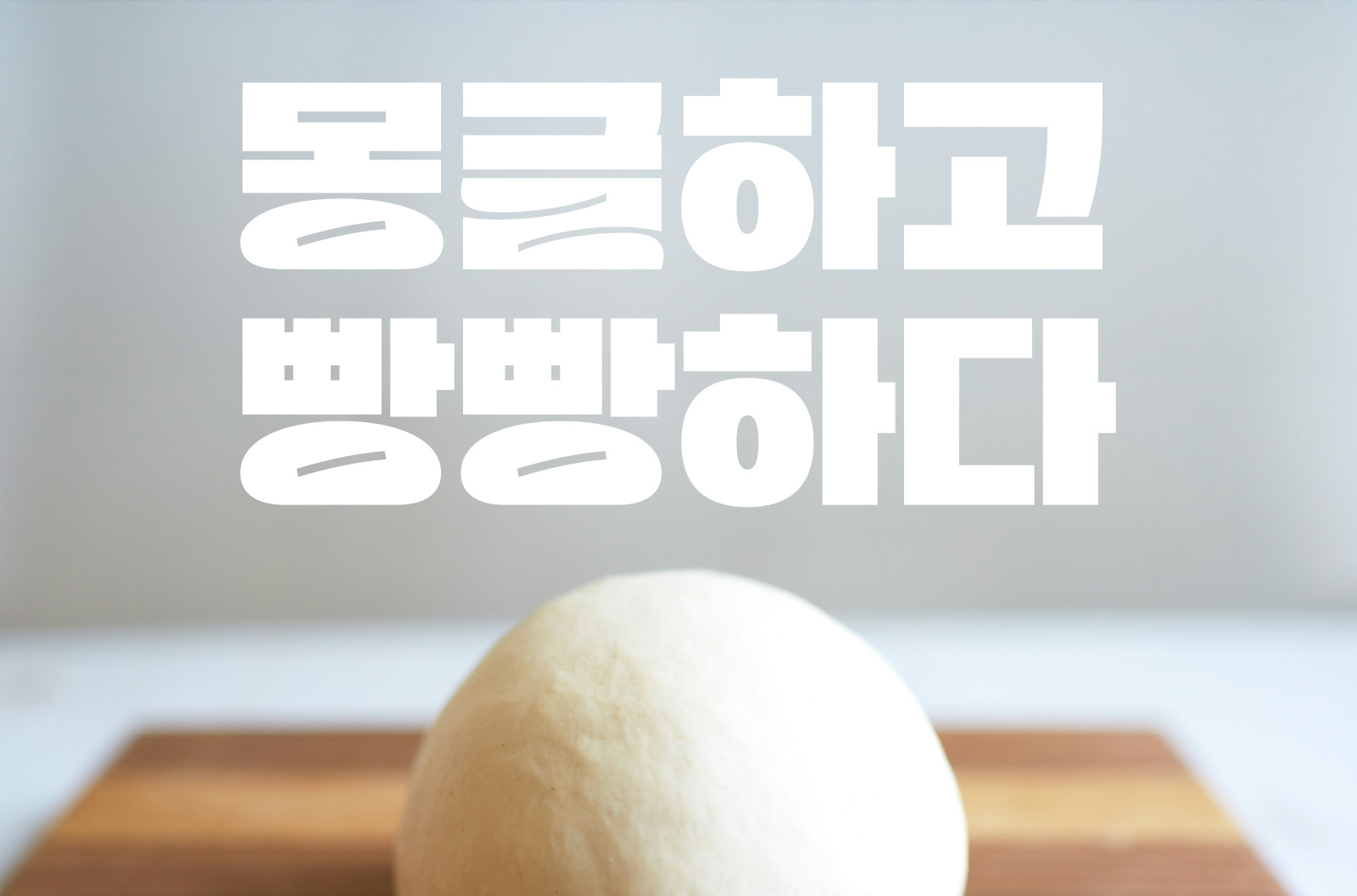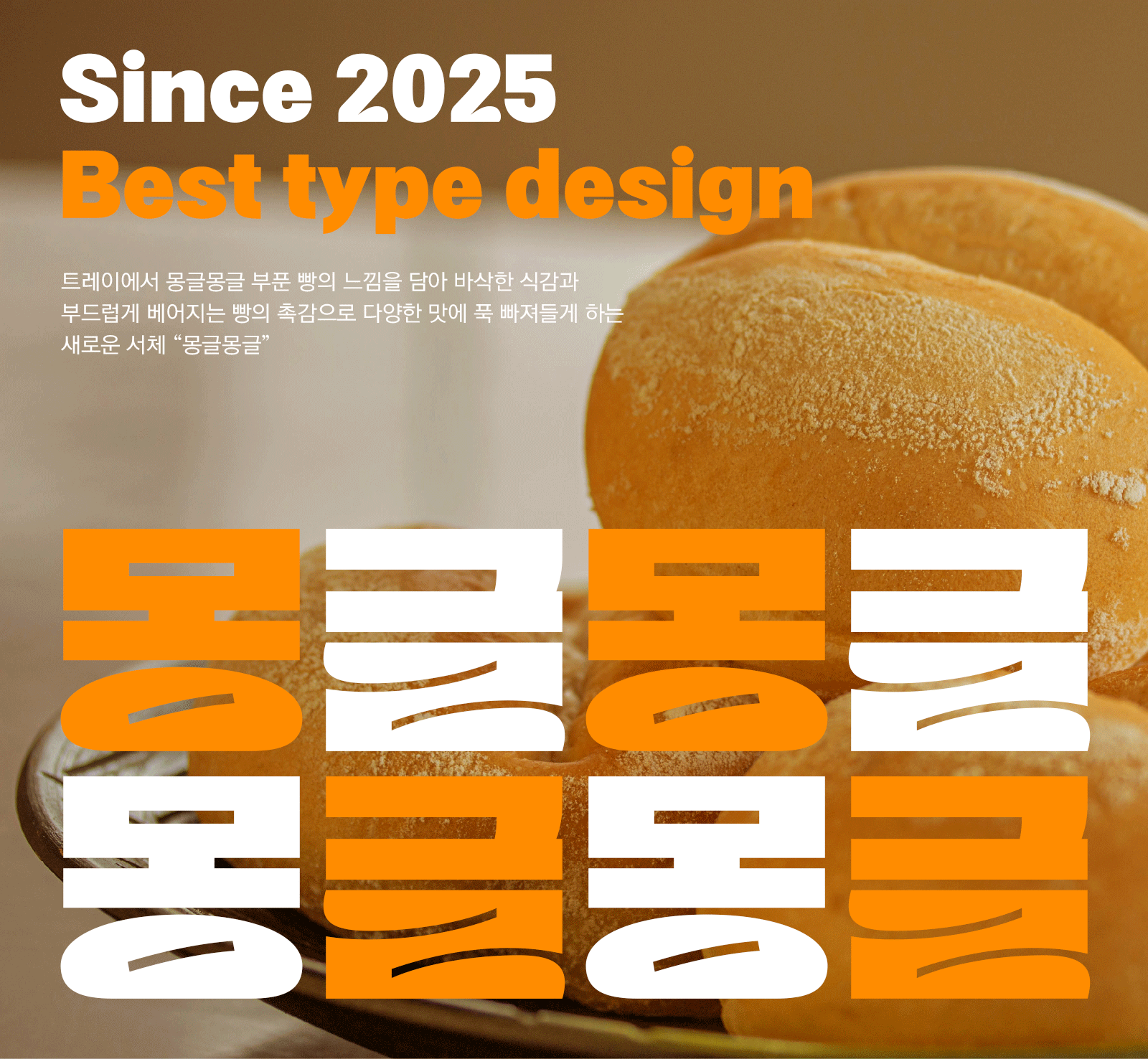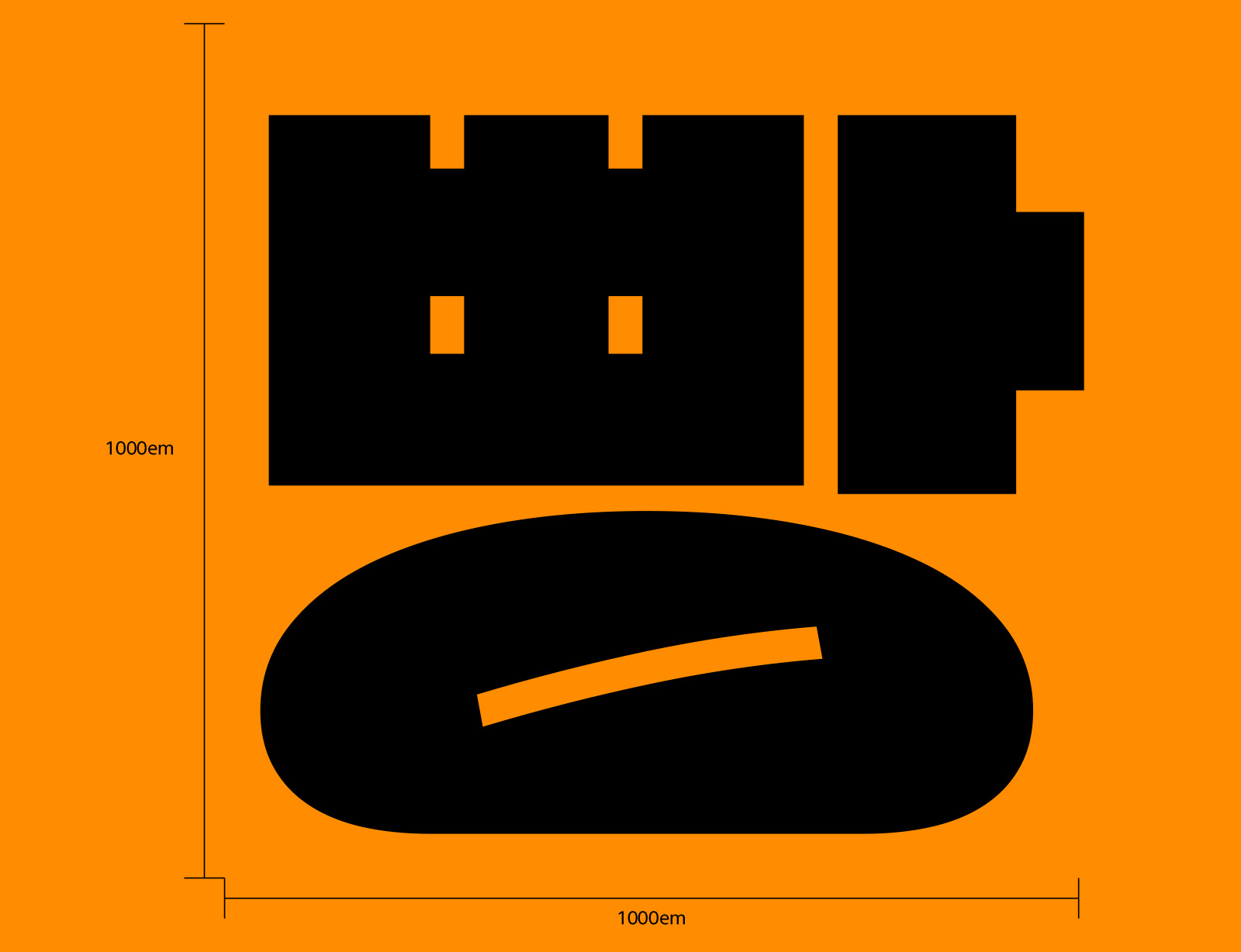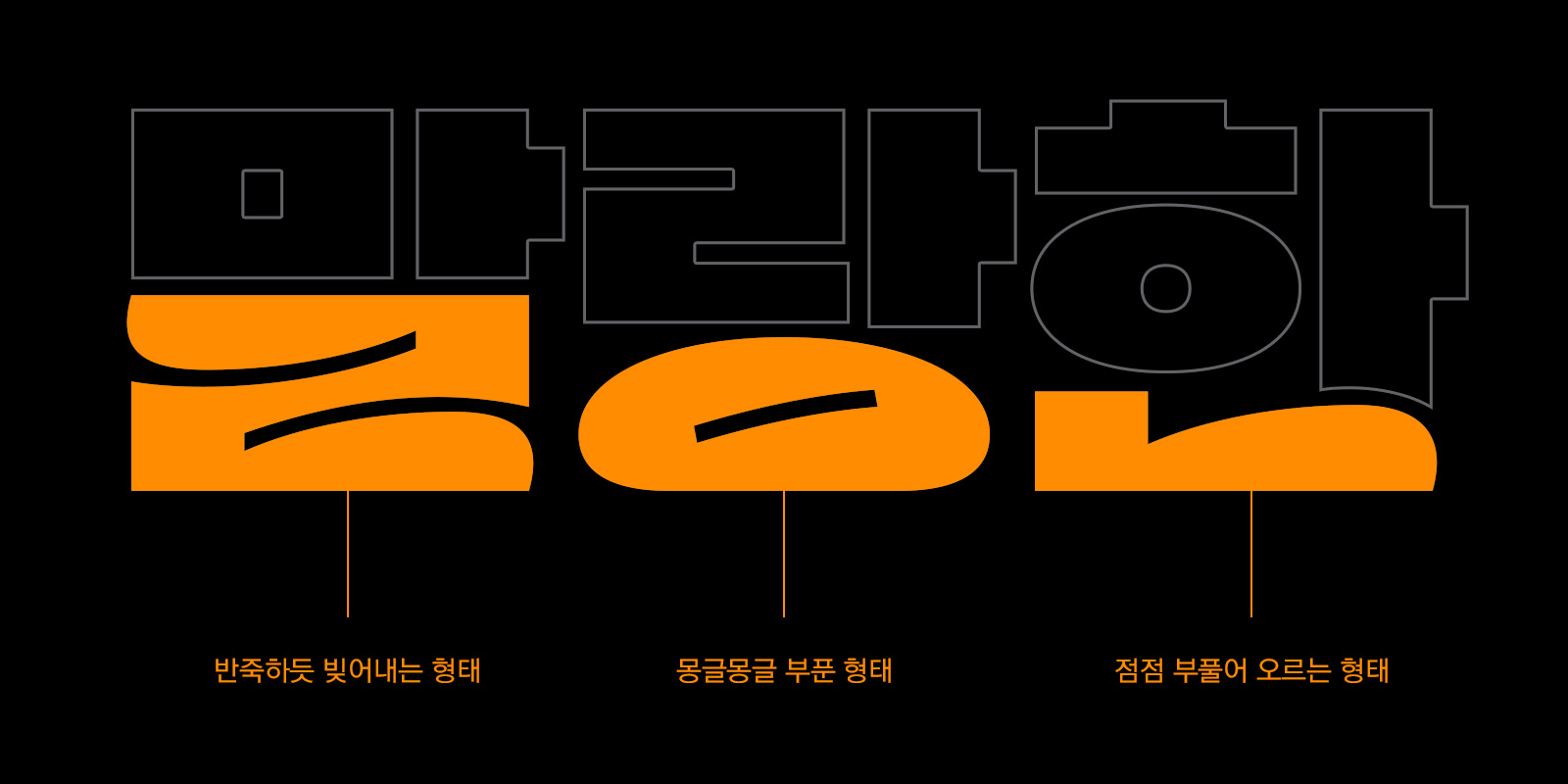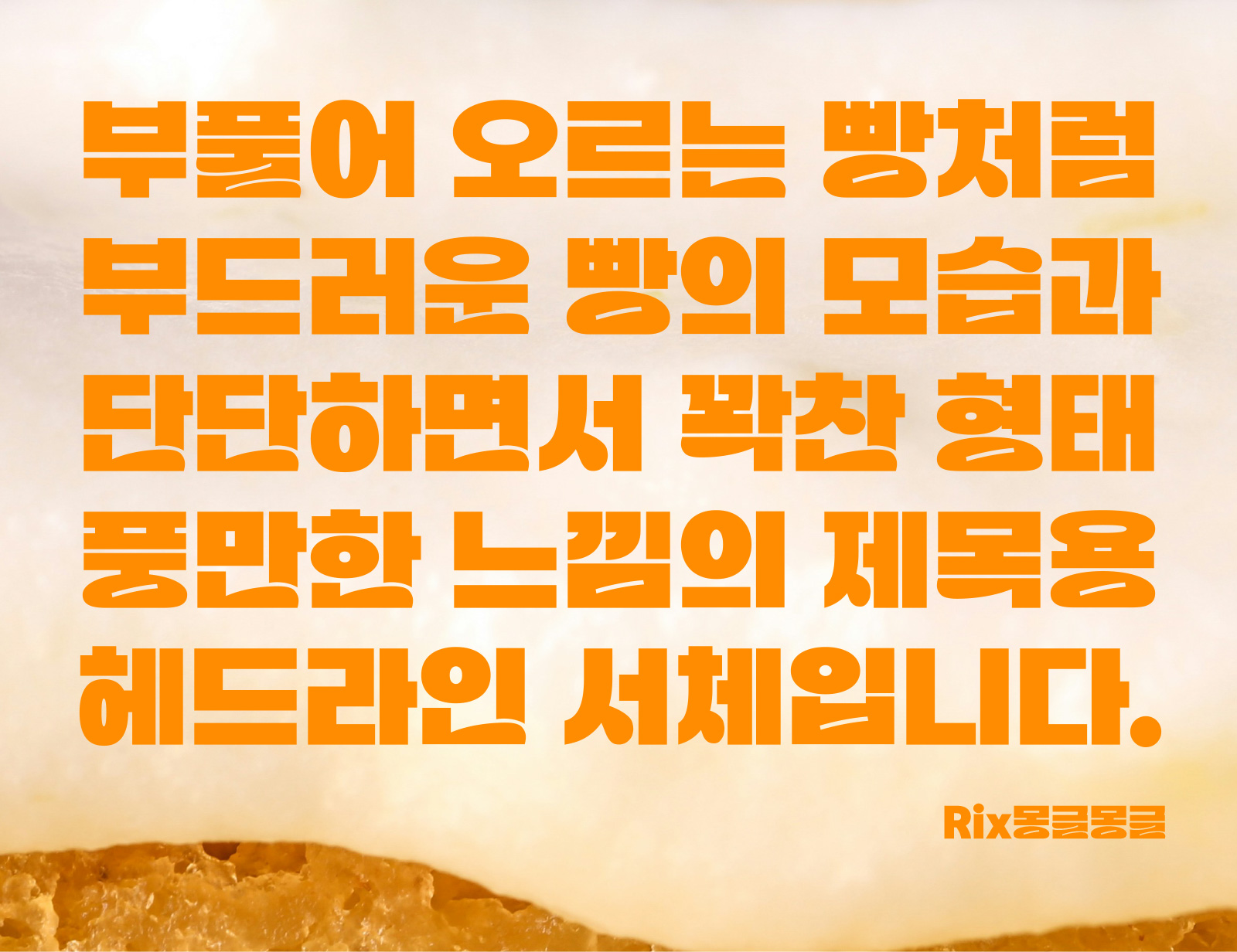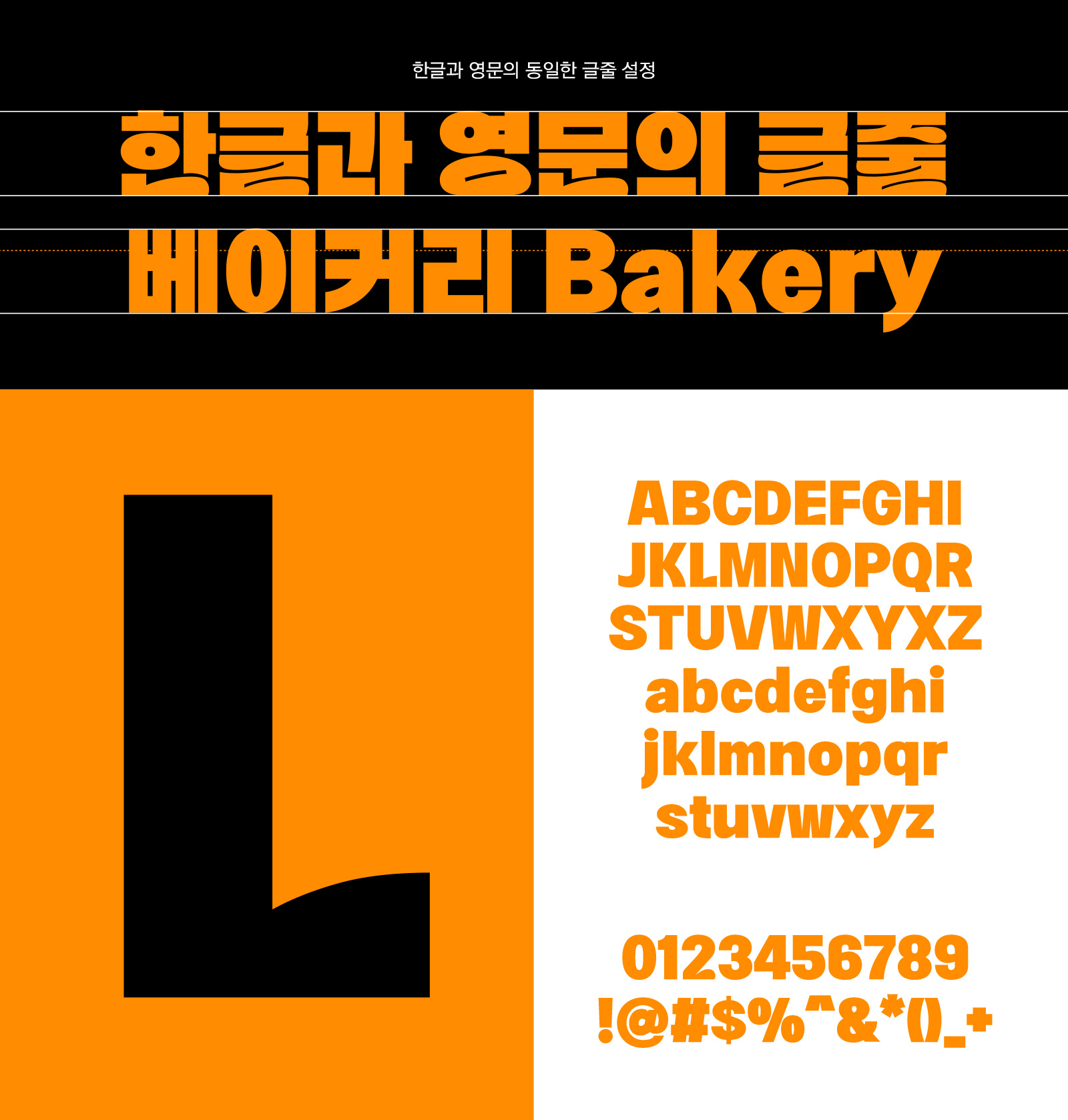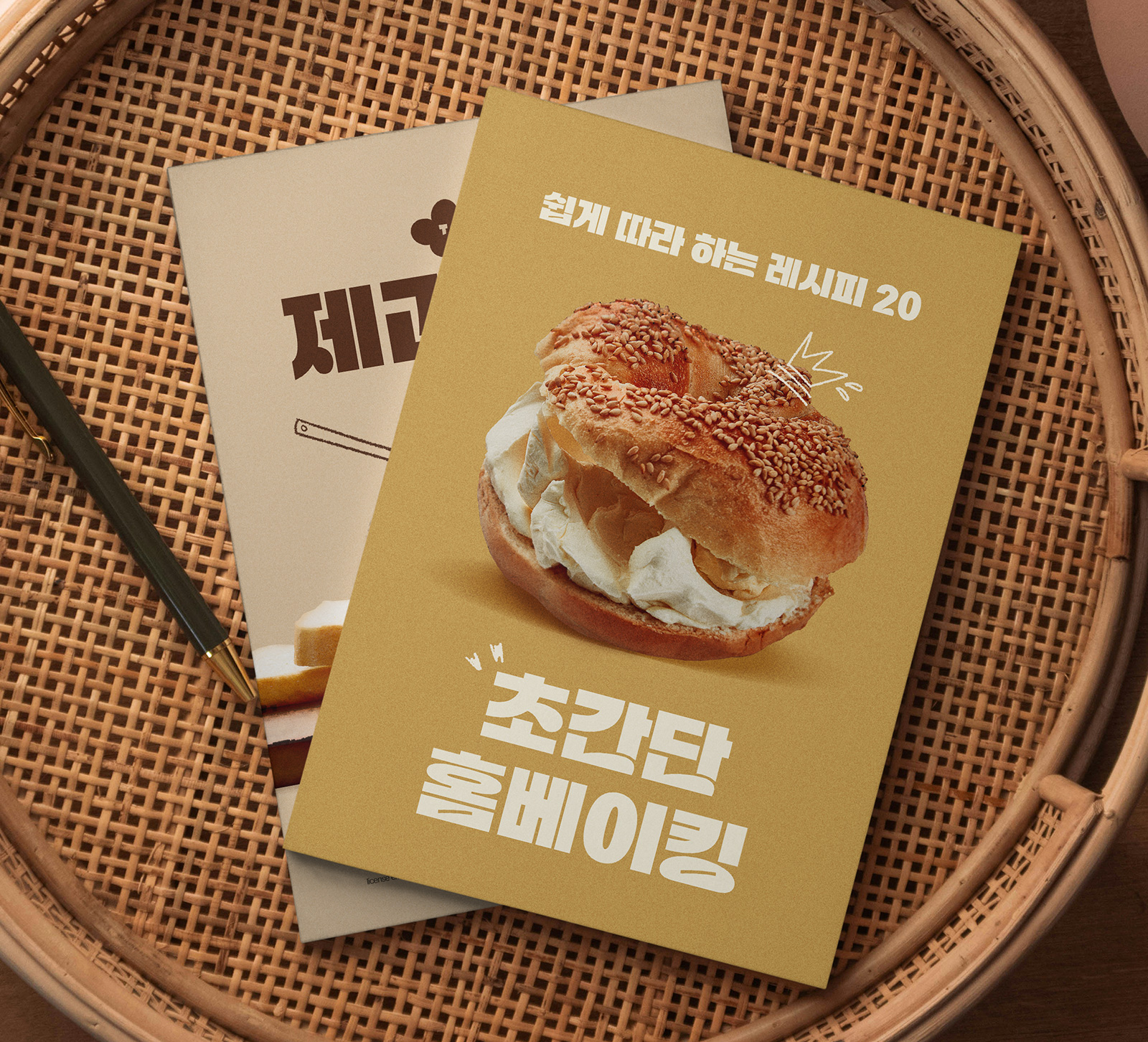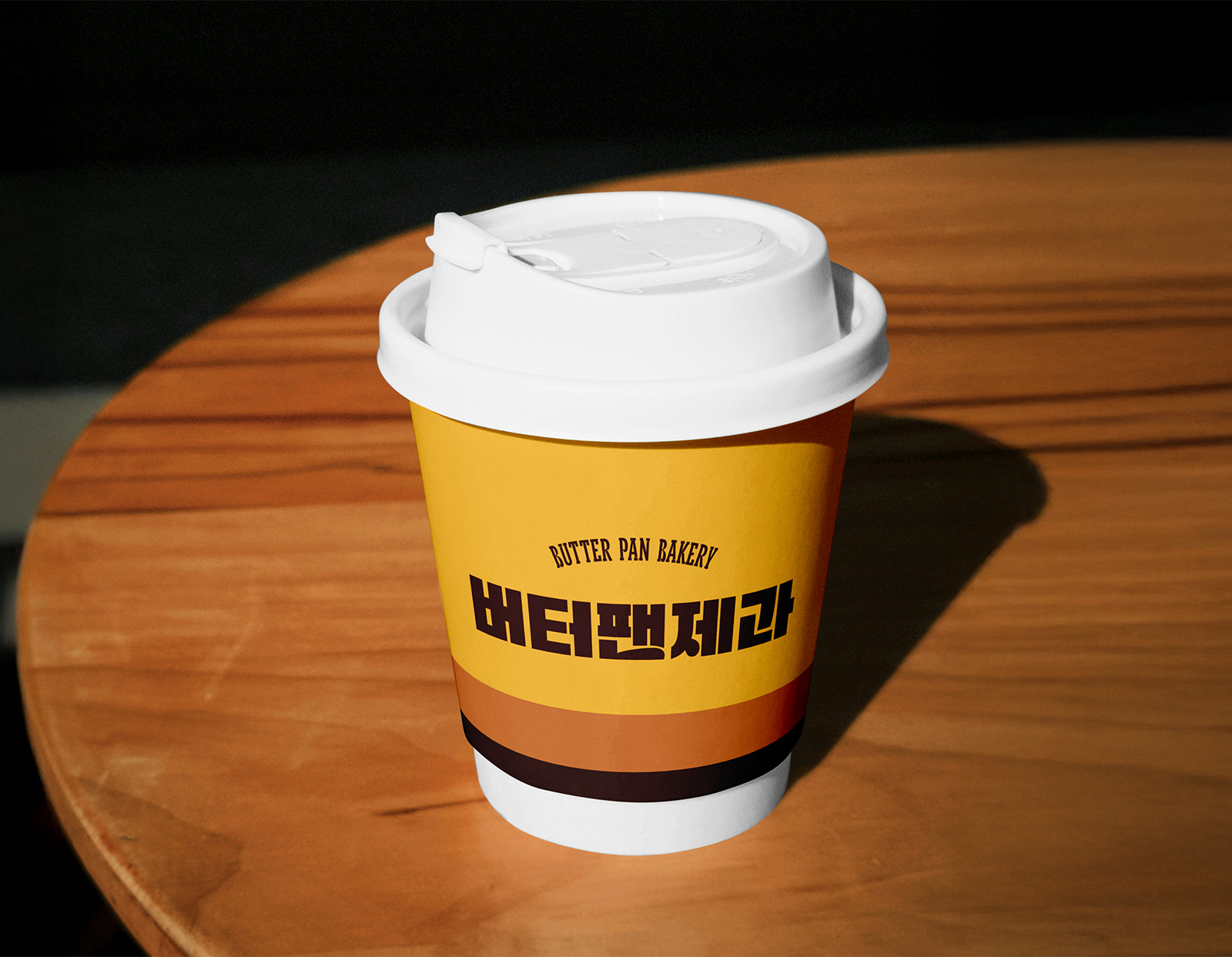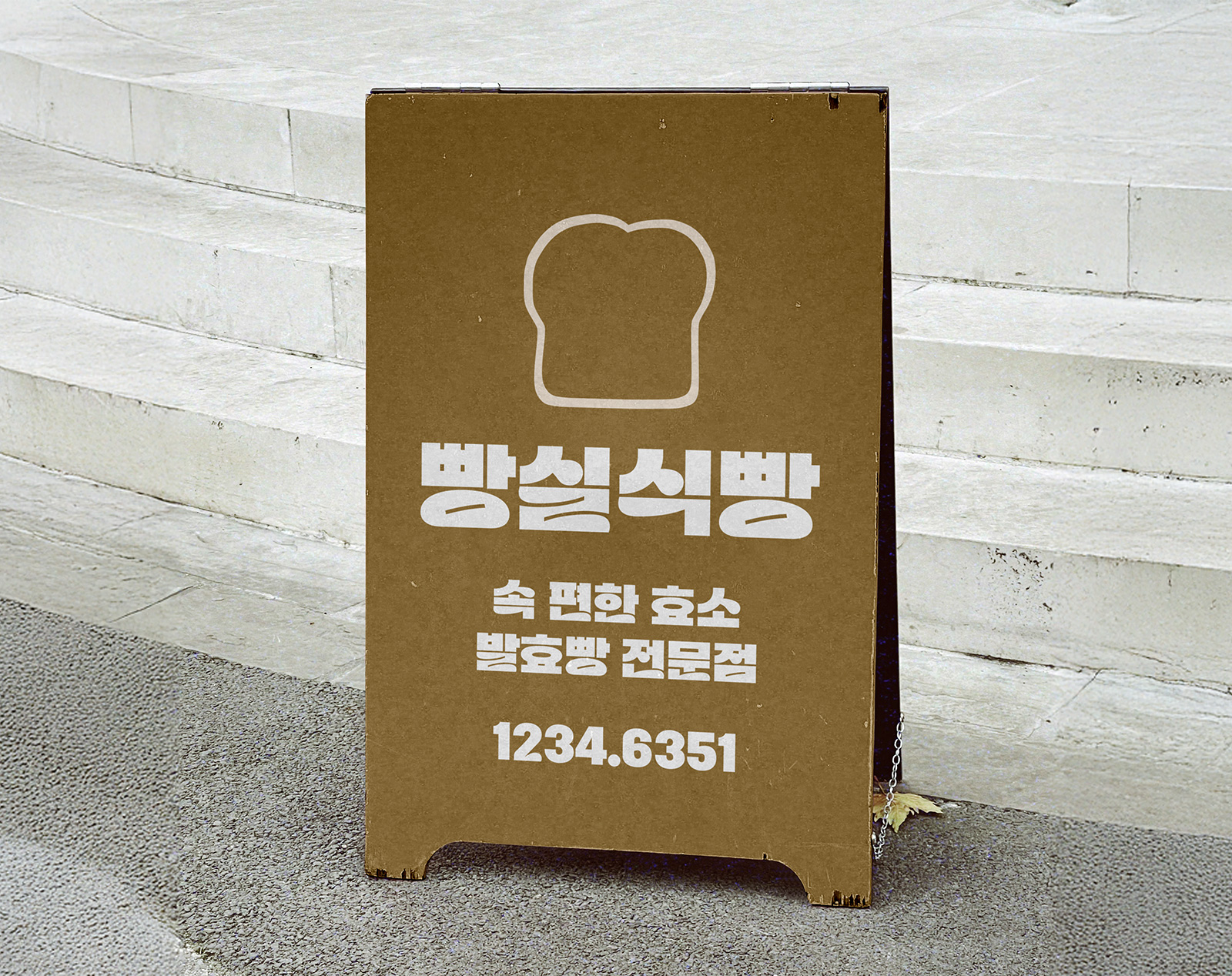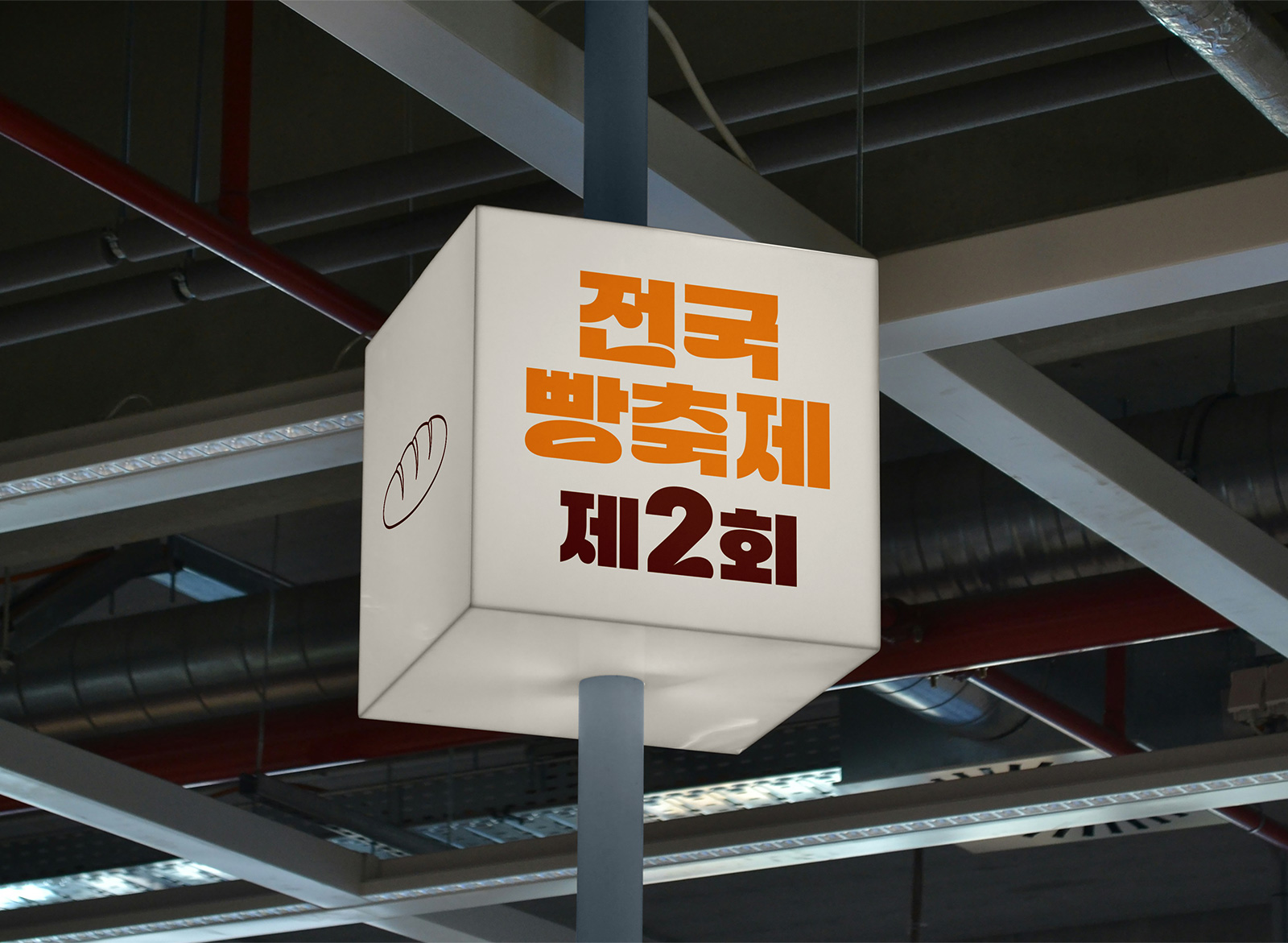
RixMongGeul
1 Style - RegularRix몽글몽글은 부풀어 오르는 빵처럼 부드러운 빵의 모습과
단단하면서 풍만한 느낌의 제목용 헤드라인 서체입니다.
| FontFamily | Rix몽글몽글 / RixMongGeul |
| Design | Kim-Jung-Jin |
| Direction | Park Yong-rak |